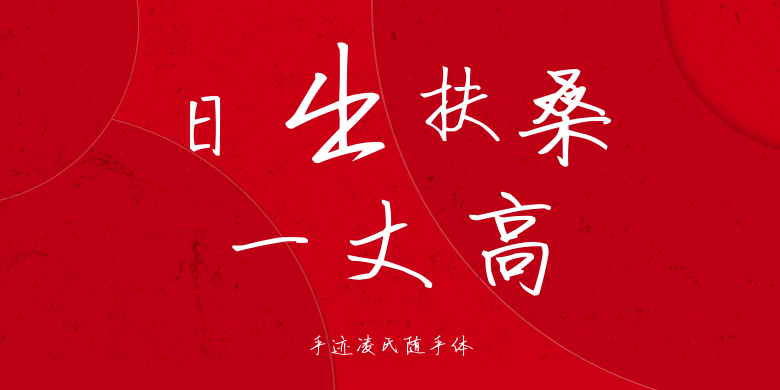
手迹凌氏随手体
手迹凌氏随手体,这款字体结构工整、笔画清晰,兼顾美观与易读性,适用于标题、正文、海报、包装、LOGO 等多种场景。字形优雅稳定,风格百搭耐看,适配日常排版与创意设计,让文字呈现更舒适、更具质感。手迹凌氏随手体一笔一画,皆是细节,以均衡的比例、流畅的线条打造舒适视觉体验,字形端正大气,风格简约现代。无论是商业设计、品牌宣传还是日常排版,都能轻松驾驭,让文字更有格调与力量。手迹凌氏随手体字体下载。